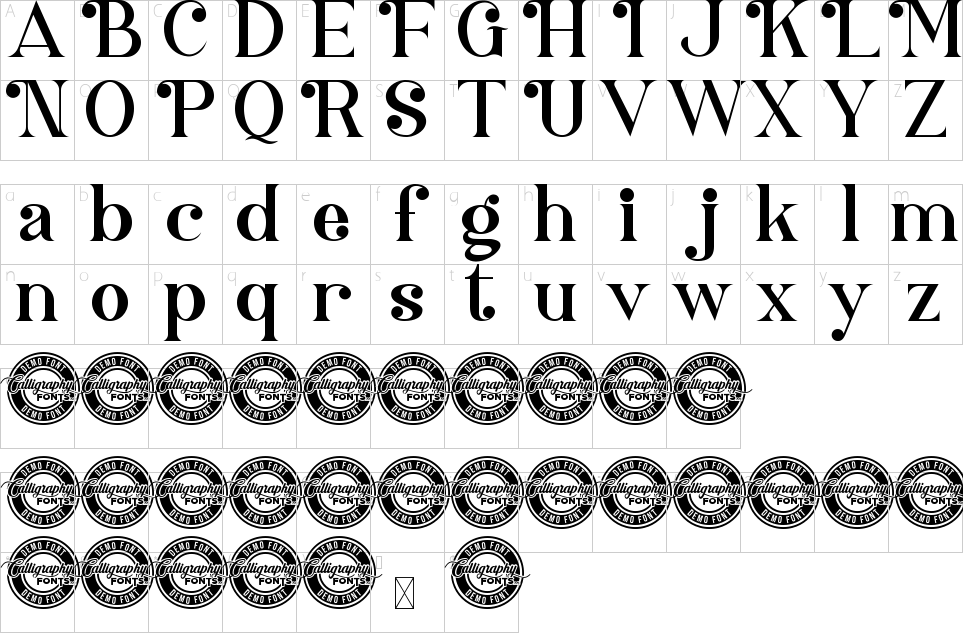
Margalitha é uma fonte elegante e versátil criada por CalligraphyFonts, disponível gratuitamente para quem procura uma fonte de qualidade para projetos em Windows e Mac. Com uma aparência minimalista e sofisticada, esta fonte é perfeita para qualquer tipo de projeto gráfico, desde letras grandes em grandes telas até subtítulos sutis em páginas web. Margalitha foi projetada para ser fácil de ler e capaz de trabalhar em uma variedade de tamanhos e estilos. Com 5,011 downloads, Margalitha já provou sua capacidade de fornecer um resultado profissional e atraente aos criadores de design. Descubra por si mesmo o poder desta fonte única.